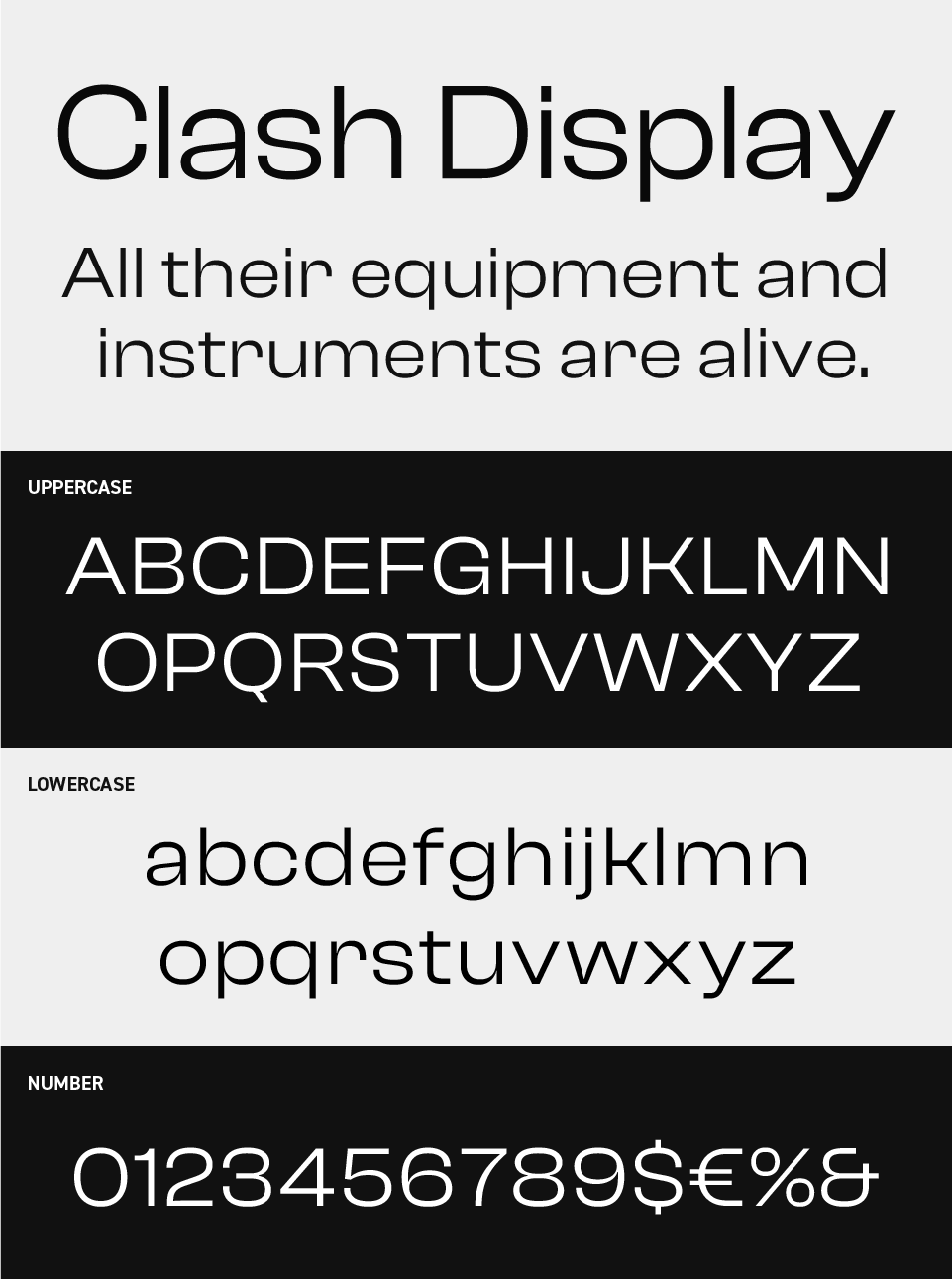
Clash Displayフォントは、ミニマルで幾何学的な構造をベースにしながらも、微妙なゆらぎや丸みを帯びた表情が特徴のサンセリフ体です。
洗練された中に、グッとして曲線がちょっとアクセントとなっており、どこかやさしさがにじむようなバランス感が魅力です。
理知的で都会的な印象がありつつ、かっちりしすぎない自然体な空気感も持ち合わせたフォントです。モダンなデザインやブランディングにフィットする、使い勝手のよいフォントです。